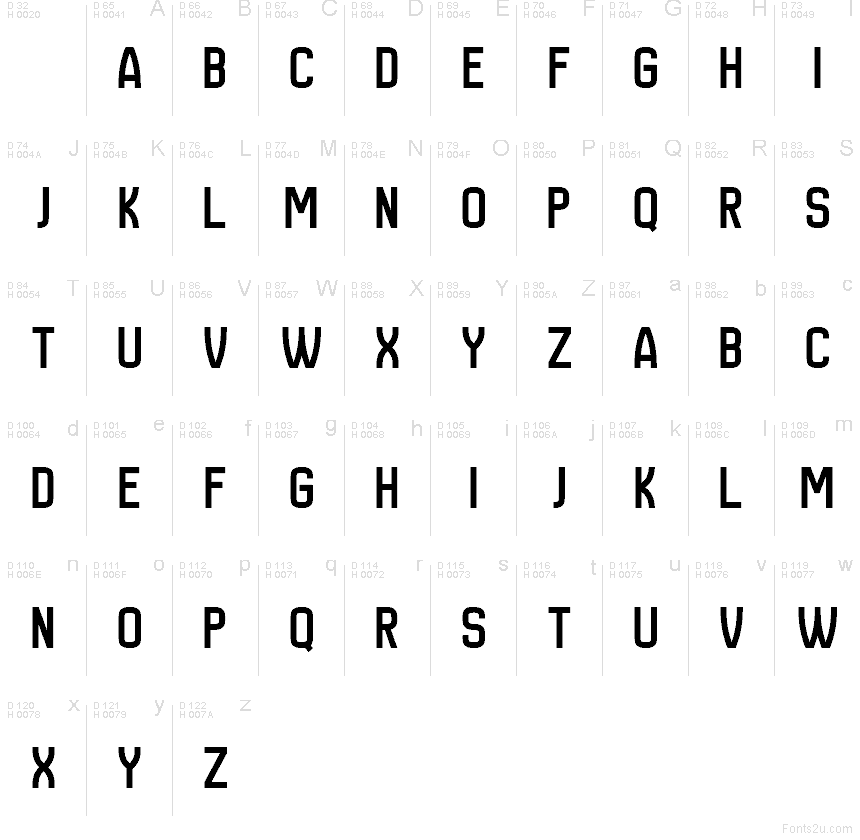
New Amsterdam Extravagant von Vladimir Nikolic ist eine kostenlose, schmale, serifenlose Schrift, die durch ihre außergewöhnlich hohe und schlanke Silhouette besticht und die Buchstaben in einen starken vertikalen Rhythmus bringt. Dieser wiederkehrende Aufwärtsdrang verleiht dem Design eine posterartige Präsenz, während die geraden Seiten und scharfen Verbindungen für eine klare, nicht ornamentale Ästhetik sorgen.
Sie ist ideal für Mastheads, Veranstaltungsplakate, Albumcover, Restaurant-Branding und Titelkarten, bei denen Höhe und Kompaktheit die visuelle Wirkung dominieren. In engen horizontalen Räumen verankert die Schrift Verpackungsfronten oder redaktionelle Überschriften, ohne ihren markanten, an eine Skyline erinnernden Rhythmus zu verlieren.